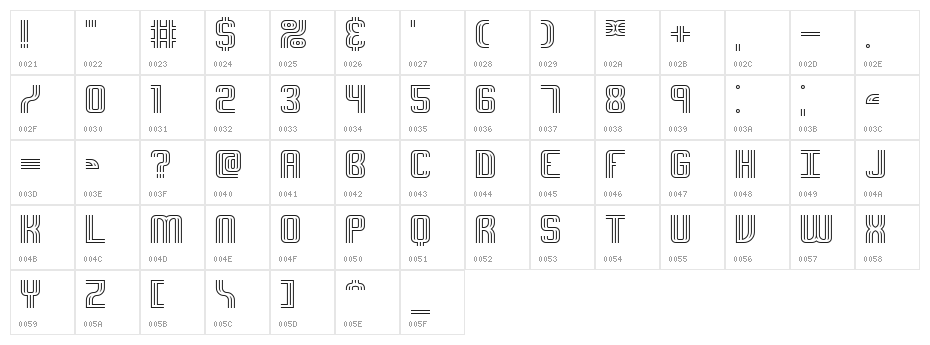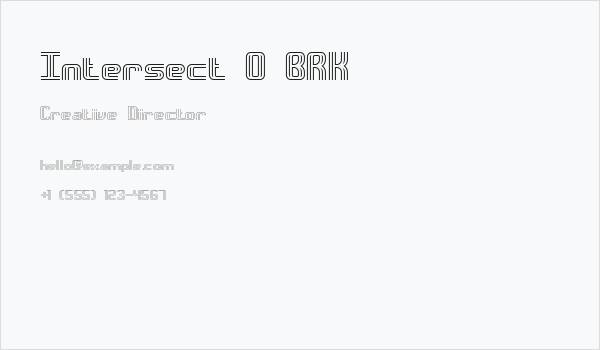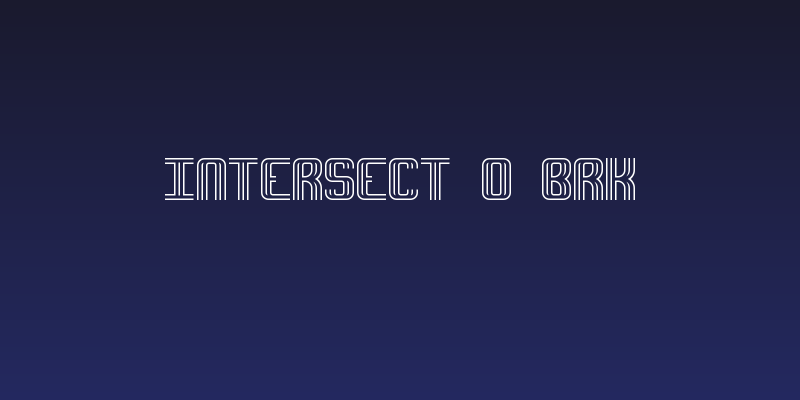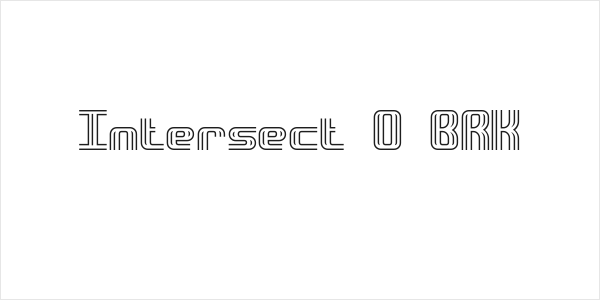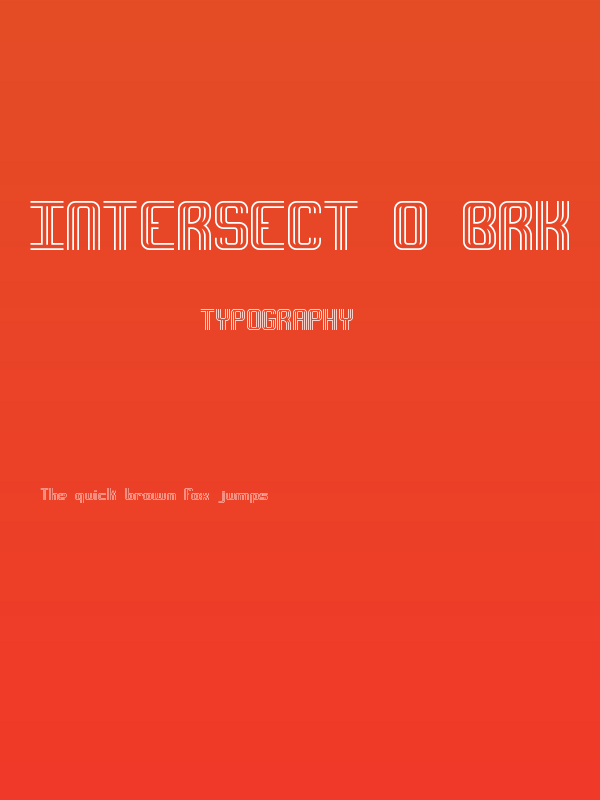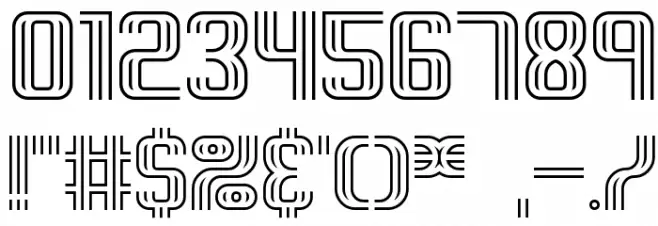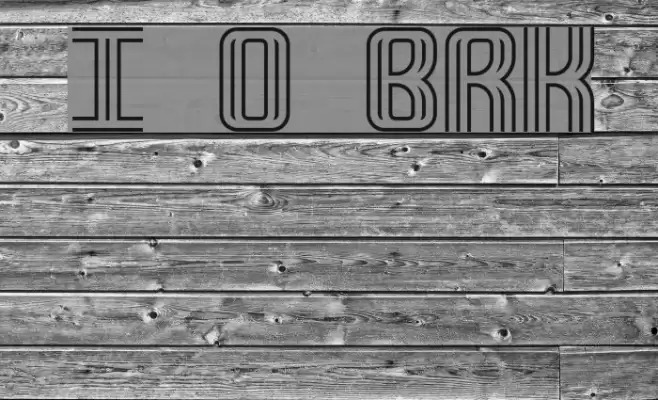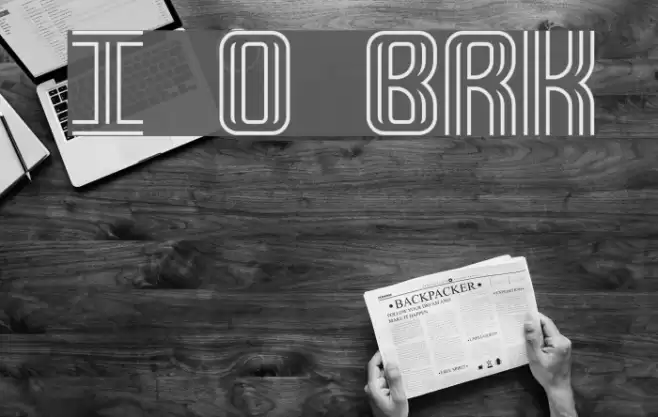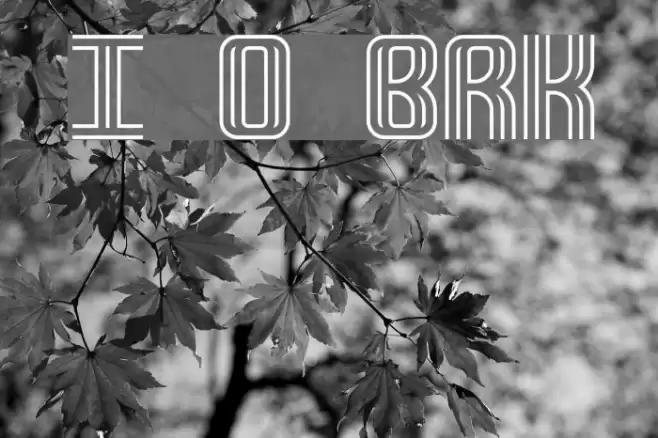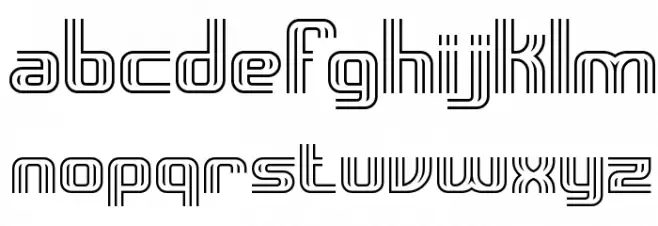
Intersect O BRK Font
| Anwendungsfall | Logos, Posters, Digital Art |
| Vorgeschlagene Projekte | Ideal for branding, posters, and digital artwork where a modern and eye-catching design is desired. |